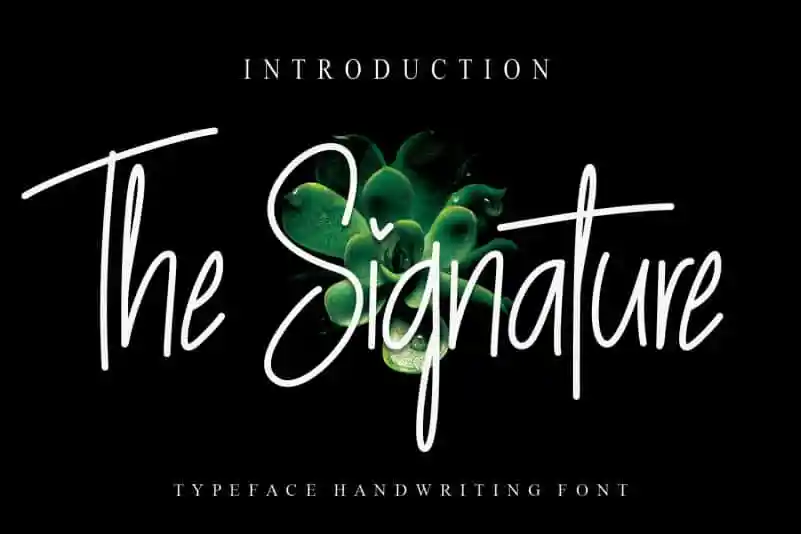
The Signature Handwritten Font – Download Grátis
Descubra a autêntica sensação de escrever com The Signature Handwritten Font, uma escolha ideal para designers que buscam uma experiência única no ambiente digital. Criada pelo designer creativeletter, esta fonte escrita à mão é perfeita para aqueles desejando dar um toque pessoal e único aos seus projetos digitais. Com traços distintivos e texturas naturais, ela oferece uma experiência de leitura agradável que se assemelha ao charme peculiar das letras escritas com a própria mão. Seja você um estilista criativo, designer gráfico ou simplesmente alguém buscando adicionar um toque único em seus documentos digitais, The Signature Handwritten Font é certamente uma opção a ser considerada para o seu próximo projeto.